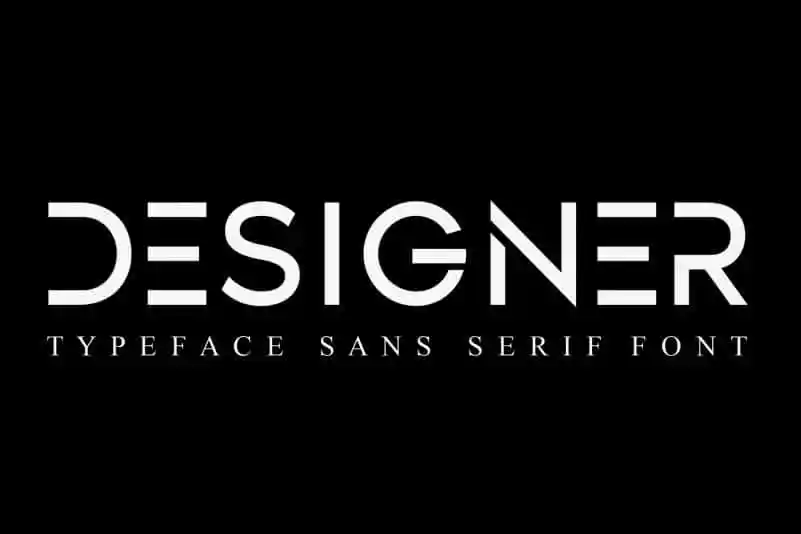
DESIGNER Display Font – Fonte Grátis
DESIGNER Display Font
Aproveite uma nova opção para suas criações digitais com DESIGNER Display Font, a marca registrada criada pelo andikastudio. Este tipo-fonte é perfeito para apresentações de slides, publicidade ou qualquer projeto que você precise destacar sua mensagem. Com linhas retas e um design limpo, este fontes sans serif oferece uma aparência moderna e atraente. Suas linhas leves e regulares também permitem um fácil legibilidade em grande tamanho, tornando-o ideal para aplicações visuais que exijam atenção de público maior. Explore o potencial desta fonte única no seu próximo projeto digital.